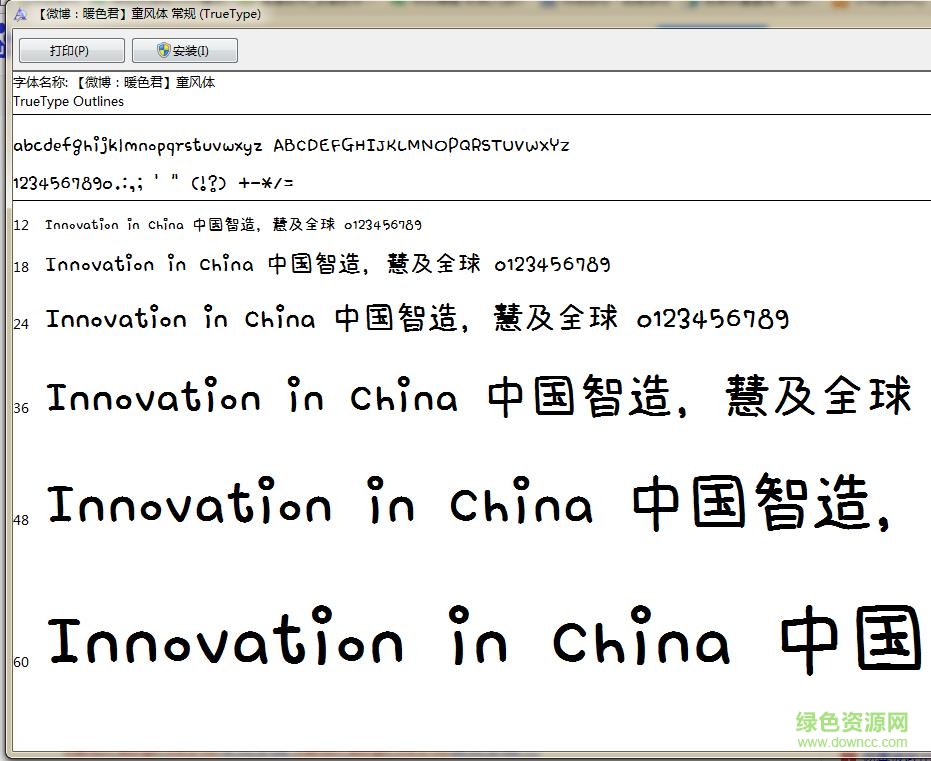
oppo童風體
童風字體小編點評
童風字體ttf字體介紹
1、大小相兼
就是每個字呈現(xiàn)大小不同,存在著一個字的筆與筆相連,字與字之間的連帶,既有實連,也有意連,有斷有連,顧盼呼應(yīng)。
2、印刷字體說明
不同的技術(shù)以及技術(shù)的不同發(fā)展階段,都會影響字體設(shè)計。顯然印刷和屏顯技術(shù)上不同,各自又都經(jīng)歷了不同的技術(shù)階段。
3、轉(zhuǎn)換為藝術(shù)字
在設(shè)計過程中,不僅要求單個字形美觀,還要使整體風格和諧統(tǒng)一,理念內(nèi)涵和易讀性,以便于信息傳播。經(jīng)過變體設(shè)計后的藝術(shù)字體,千姿百態(tài),變化萬千,是一種字體藝術(shù)的創(chuàng)新。